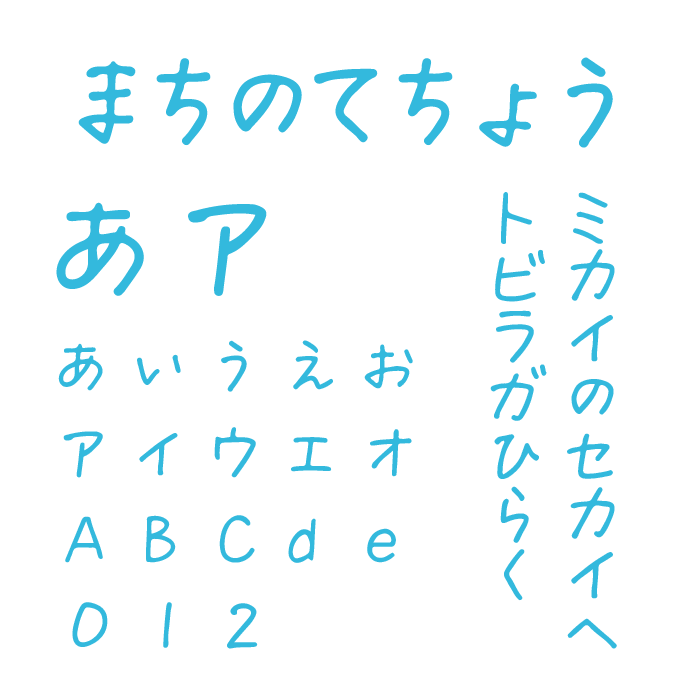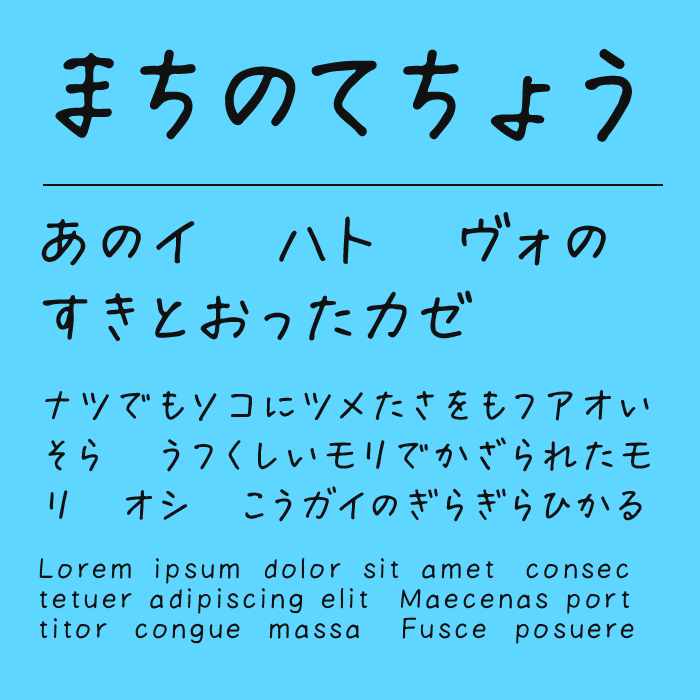
まちのてちょうフォントは、気取らず素朴で、あたたかみのある手書きスタイルが魅力のフォントです。
文字が交差している部分は、墨溜まりのような質感があり、角がやや丸くなめらかで、ひらがなやカタカナは特にやさしく見える形に整えられている可愛らしい手書きフォントです。
親しみやすさと視認性を兼ね備えており、イラスト付きのメモ、町案内、SNS投稿画像などにぴったりなフォントです。日記やノートのような感覚をそのままデザインに持ち込みたいときに重宝します。フォント自体に「暮らし感」があり、見る人の心を少しホッとさせるような効果をもたらしてくれるフォントです。
収録文字は、ひらがな・カタカナ・アルファベット・数字が収録。無料版には、漢字収録はありませんが、漢字も幅広くカバーされている「まちのてちょう 通常版」もあります。